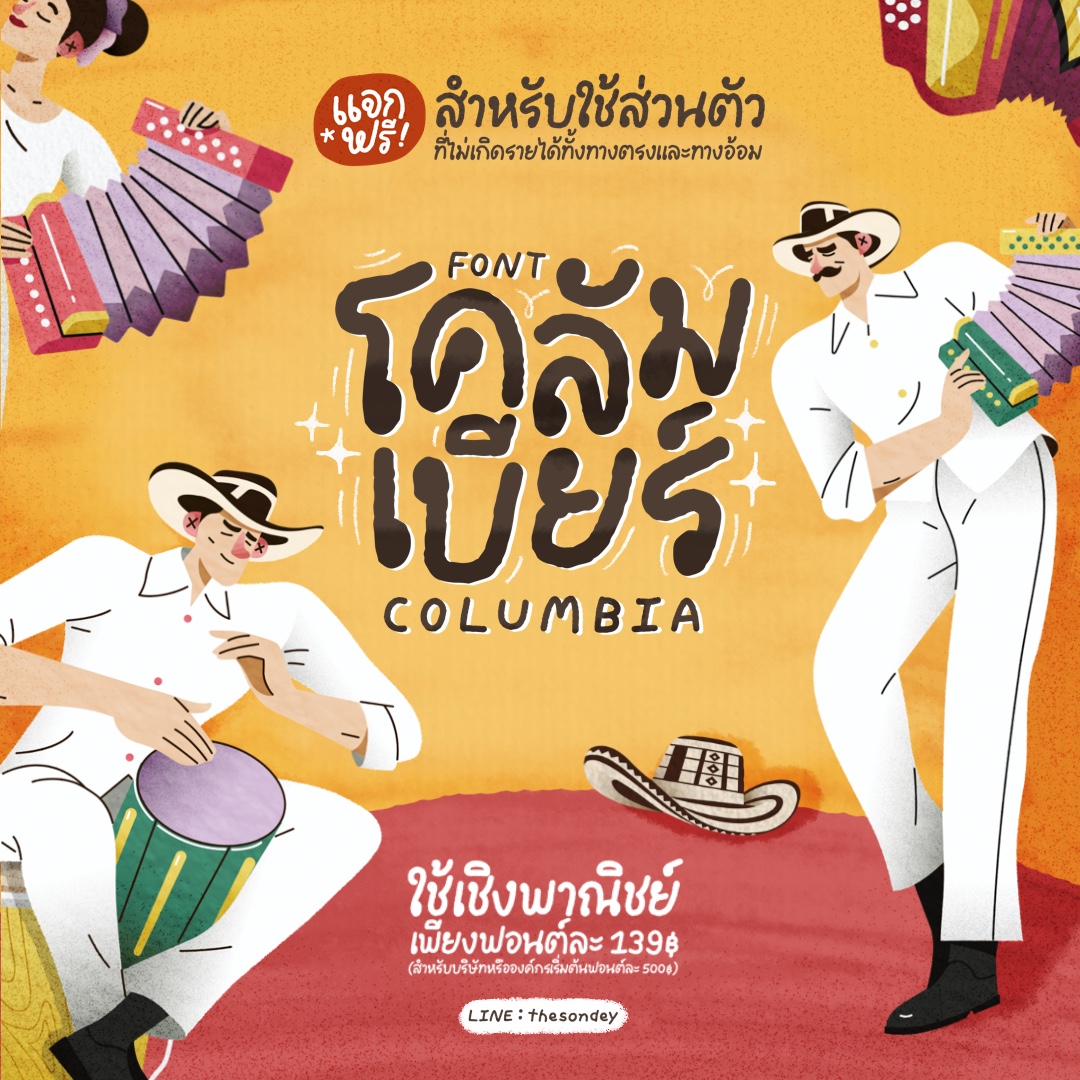
โคลอมเบียร์ (PG Columbia)
ฟอนต์ลายมือสไตล์น่ารักปุ๊กปิ๊ก อ่านง่าย รองรับ Microsoft, Photoshop, Illustrator, CapCut, ibisPaint, Procreate, Good Note และแอปฯ ต่างๆ ที่มีให้ติดตั้งฟอนต์